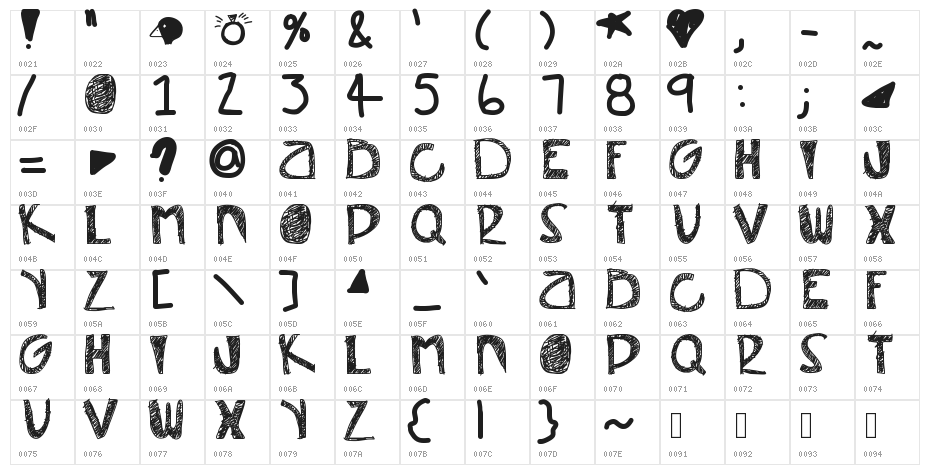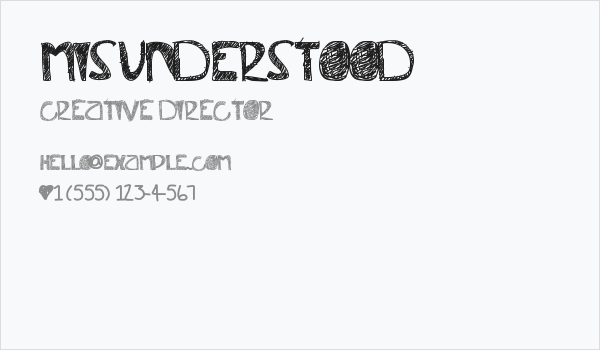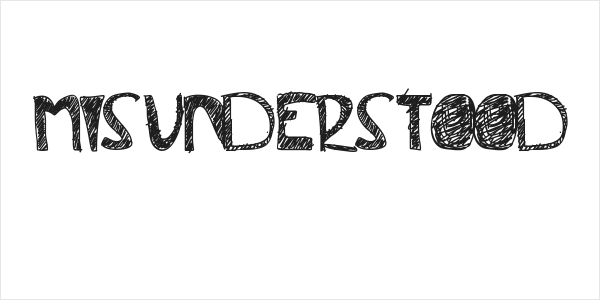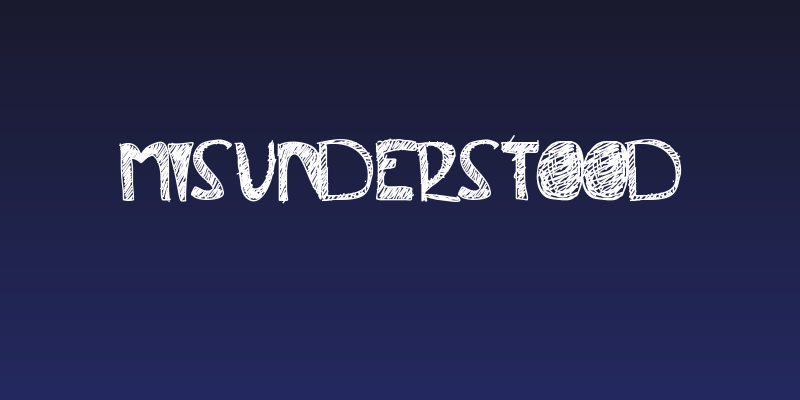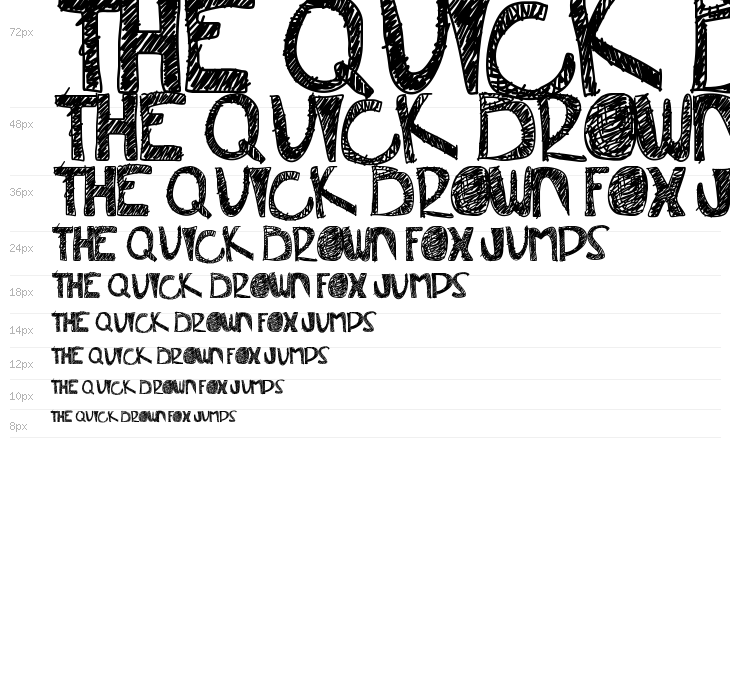
Misunderstood Font
| Stile generale | Playful, Creative |
| Caso d'uso | Headlines, Posters, Creative projects |
| Progetti proposti | Ideal for children's books, comic strips, playful branding, and creative posters. |